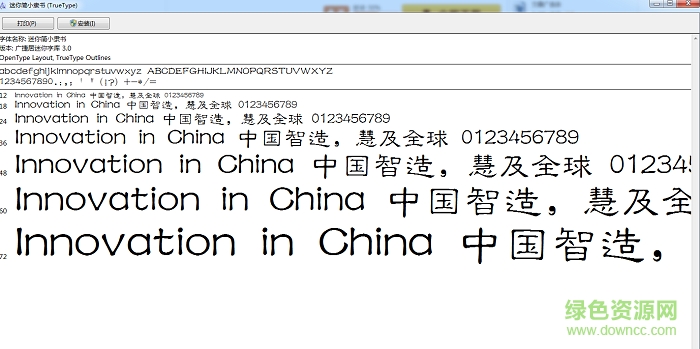
jxiaolisu 是什么字體?jxiaolisu是一款迷你小隸書字體,該字體結(jié)構(gòu)協(xié)調(diào),嫻靜沉穩(wěn)卻不呆板,實用性強,不論用在排版還是設(shè)計方面都不跌份,讓大家在進行書面排版的時候能夠多一項字體的選擇,也許效果會更好哦,感興趣的就來綠色資源網(wǎng)下載使用吧!